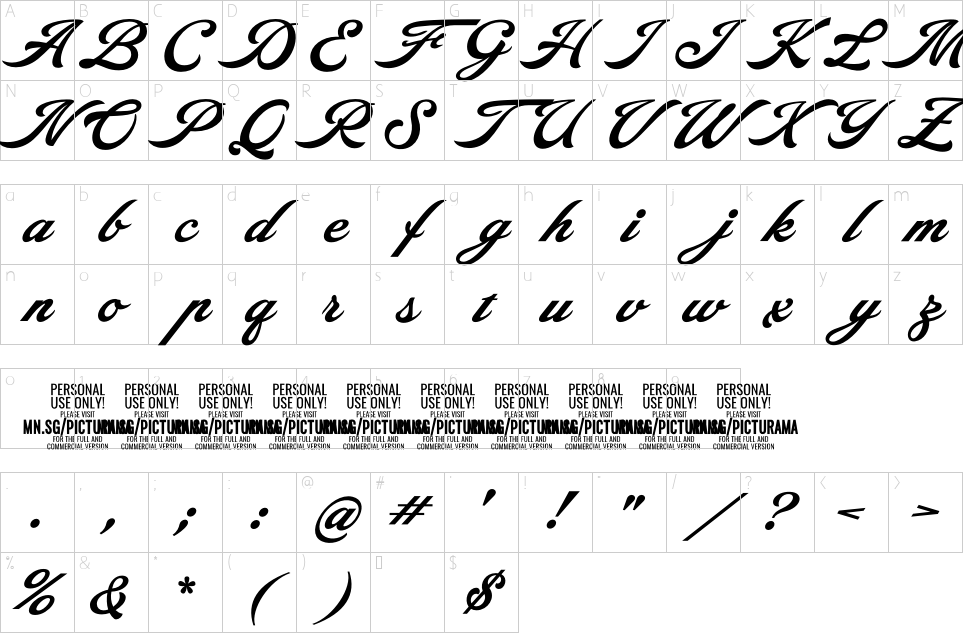
Picturama Founder Font | 1001 Free Fonts – Fonte Grátis
A fonte Picturama Founder é um deslumbrante acervo de letras que traz um toque de elegância e originalidade para seu design. Desenhada pelo talentoso Måns Grebäck, esta fonte foi criada com um estilo único que é perfeito para os projetos de design gráfico. A Picturama Founder é uma opção excelente para quem busca uma fonte única e versátil. E embora tenha sido desenvolvida para os amantes de design que desejam personalizar suas criações, ela também é uma escolha perfeita para designers gráficos profissionais. Com a Picturama Founder, você terá a oportunidade de adicionar um toque único e diferenciado a qualquer design. Sua disponibilidade gratuita, para uso tanto em sistemas Windows quanto Mac, torna-a uma fonte de primeira escolha para projetos de design, não importa o tamanho ou a natureza do seu projeto.